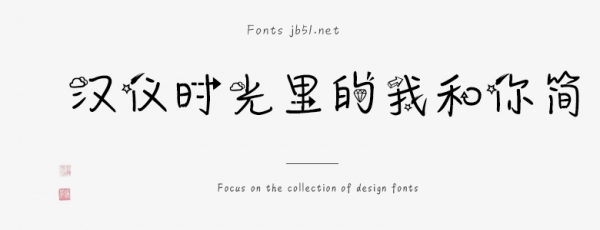
漢儀時光里的我和你簡是由漢儀字庫出品,字體筆觸適中,字形端正,以云朵,星星卡通圖案作為點(diǎn)綴,具有很好的視覺感,適合應(yīng)用于藝術(shù)設(shè)計(jì)、平面宣傳設(shè)計(jì)、網(wǎng)頁設(shè)計(jì),書法字帖等領(lǐng)域,需要的朋友可以前來本站下載。